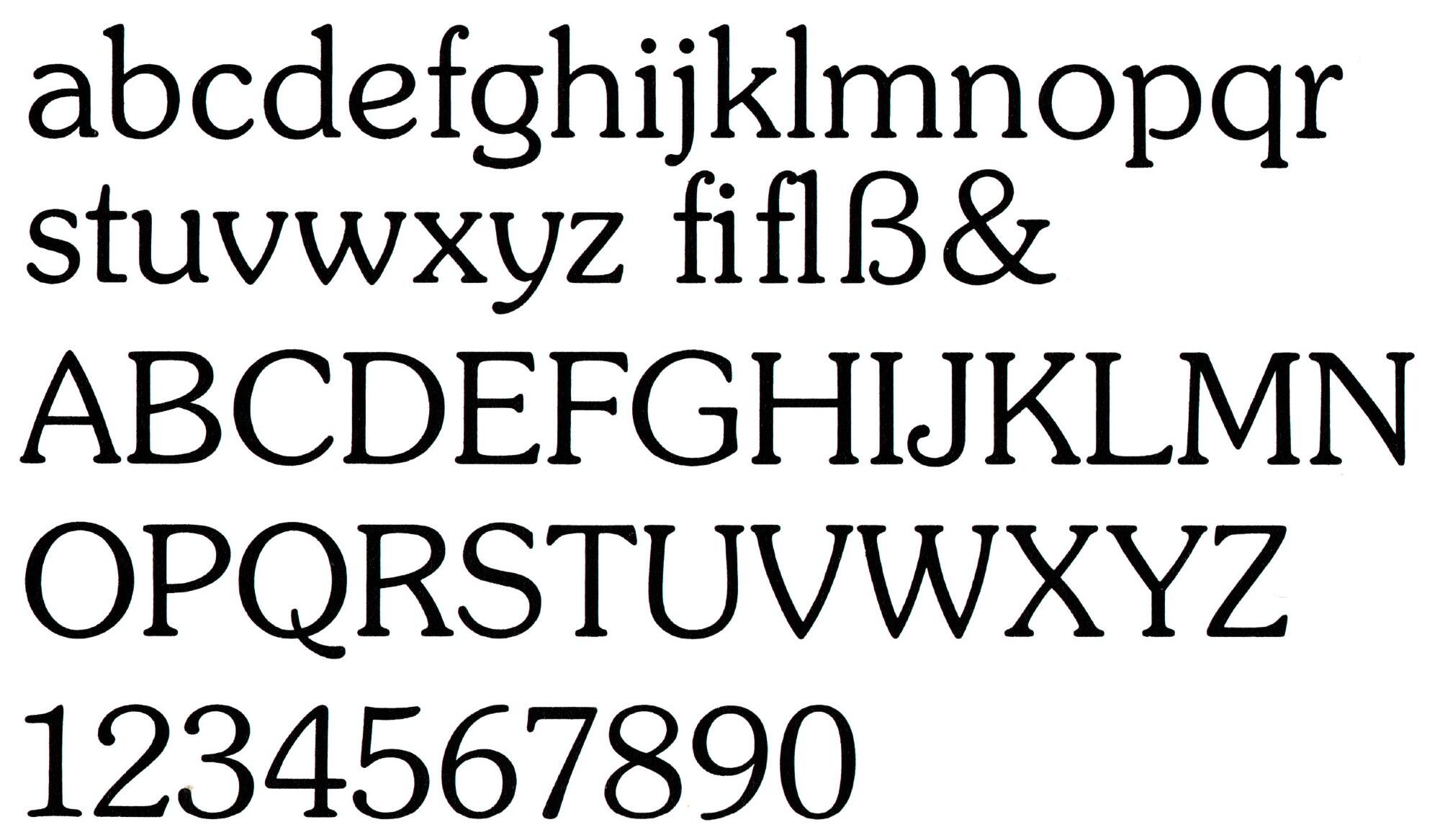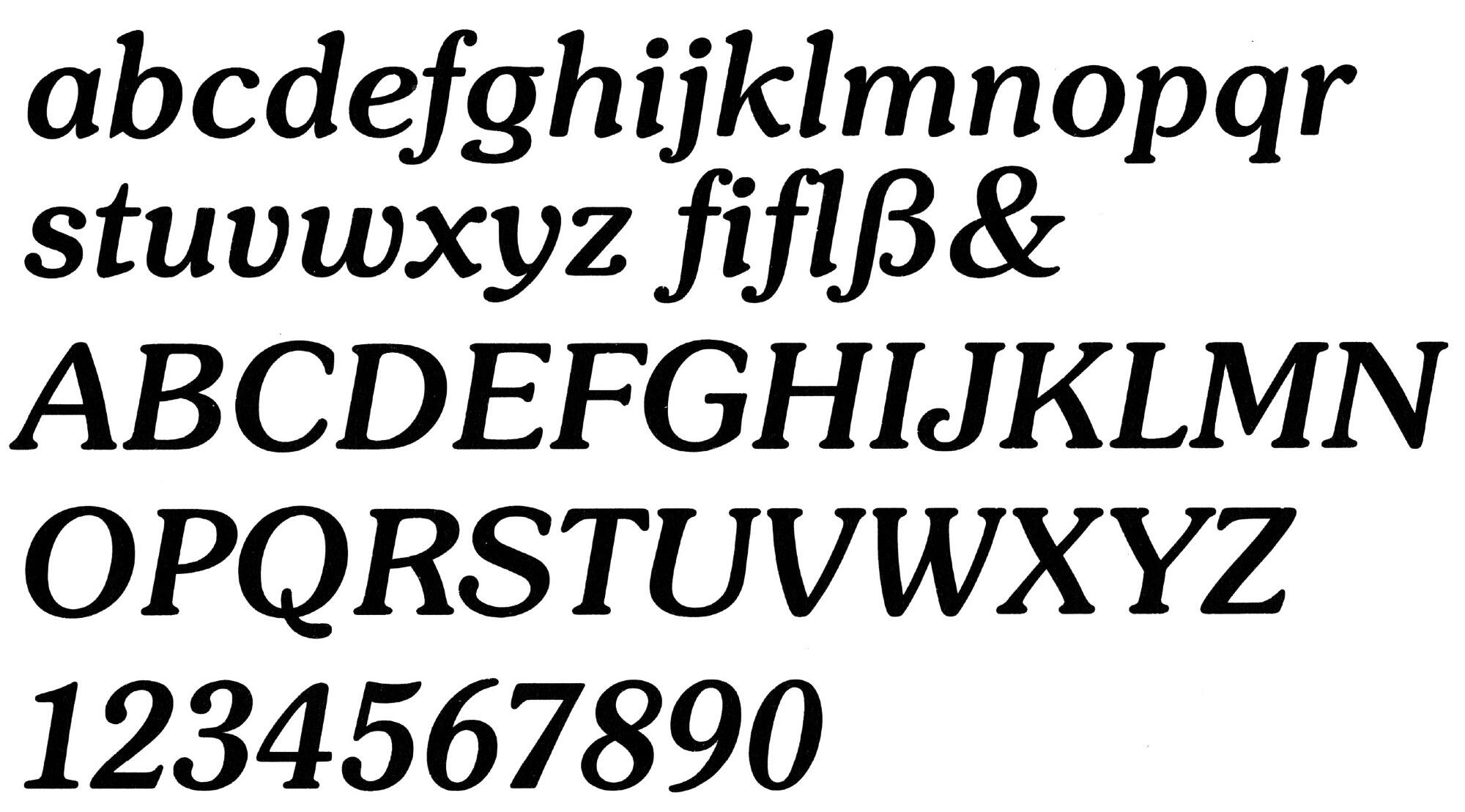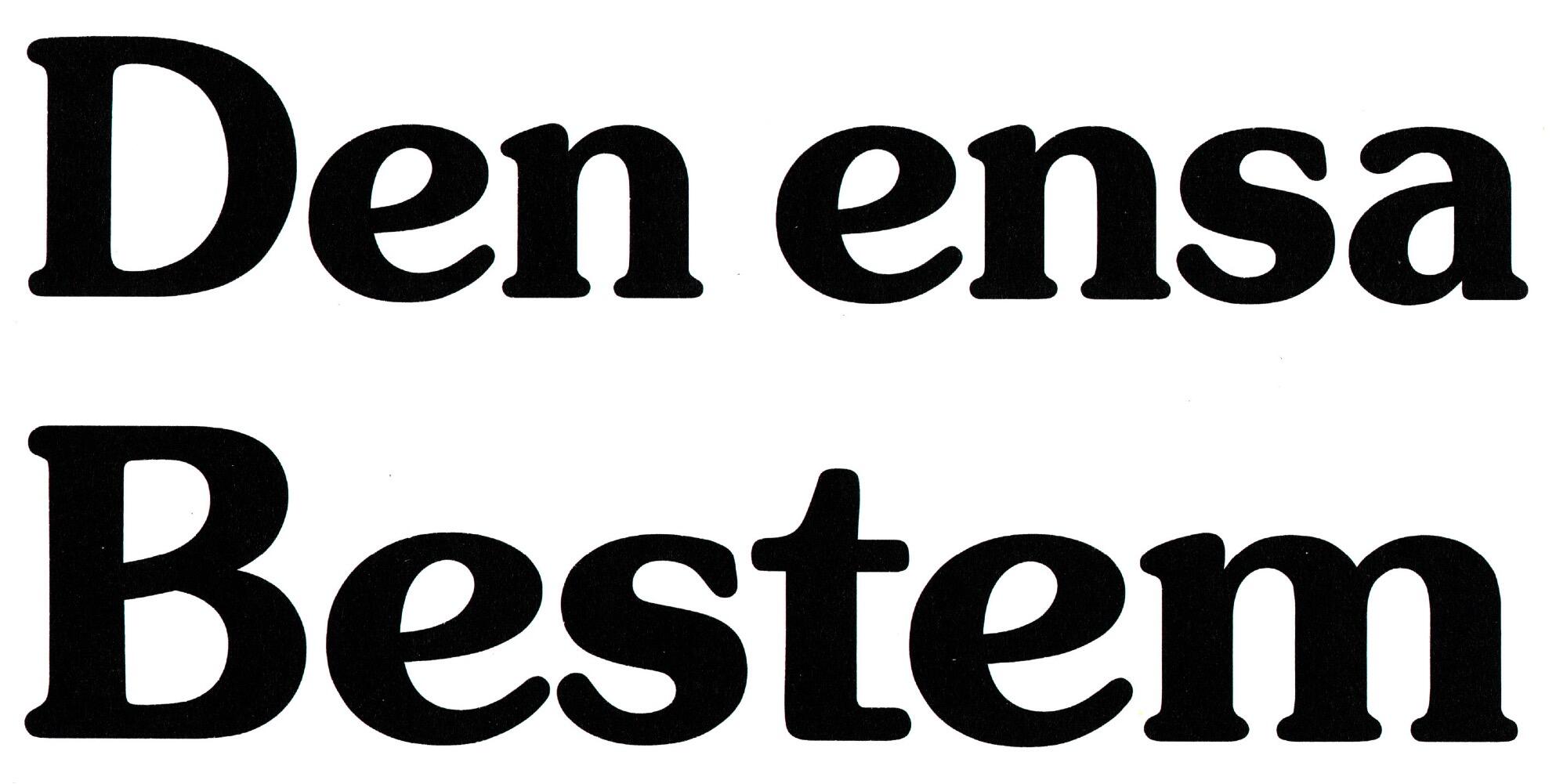
Die Souvenir wurde Anfang des 20. Jahrhunderts von Morris Fuller Benton für ATF gezeichnet. Die Schrift zeigt viele Ähnlichkeiten zur deutschen Schelter-Antiqua, die einige Jahre zuvor entstand. In den 1960er-Jahren wurde die Souvenir von Ed Benguiat für die Photo-Lettering Corporation neu aufgelegt. Anfang der 1970er-Jahre brachte ITC die Schrift heraus und ließ sie von Ed Benguiat um weitere Schnitte erweitern. In den 1970er-Jahren war die Schrift äußerst erfolgreich und wurde für die meisten Fotosatzsysteme angeboten. Selbst eine Version für den langsam außer Gebrauch geratenden Linotype-Maschinensatz wurde noch einmal angefertigt.
Die Digitalisierung von ITC ist heute in vier Strichstärken mit zugehörigen Kursiven verfügbar.